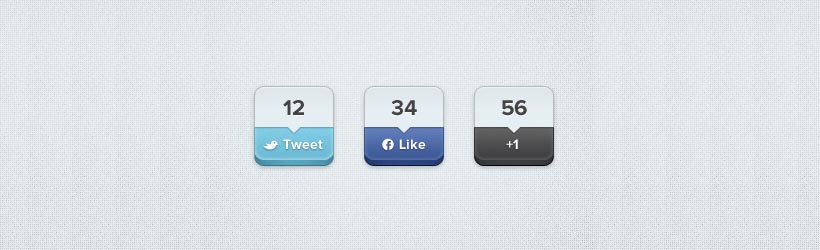
Font Inspiration: Kelson
Kelson è un font molto sinuoso ed elegante capace di esaltare web design raffinati e creativi. Scopriamo insieme l’anteprima del font.
Ecco una comoda anteprima di Kelson: